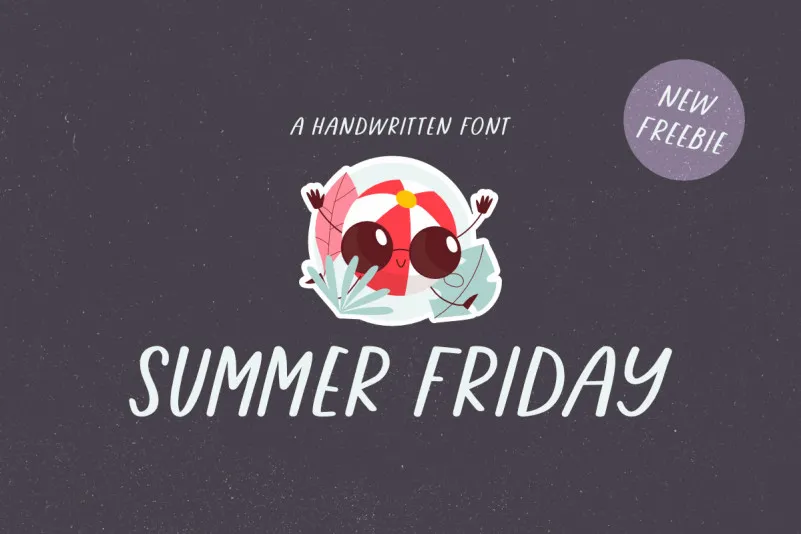
Aqui está uma breve descrição em português para a página de download da fonte ‘Summer Friday Font’: Descubra alegria no seu próximo projeto com o ‘Summer Friday Font’, uma fonte leve e divertida desenvolvida pelo designer jimtypestudio. Através de seus traços elegantes e tipografia cursiva, você pode personalizar mensagens de felicitações, convites e frases memoráveis para um toque único e alegre. A fonte ‘Summer Friday Font’ está disponível em todas as letras maiúsculas, garantindo uma aparência clean e moderna que se adequa perfeitamente a vários propósitos. Seja para criar mensagens de felicitações para festas ou eventos especiais, criar design de merchandising personalizado ou apenas adicionar um toque especial a qualquer projeto em seu dia a dia. A ‘Summer Friday Font’ é uma escolha inteligente para quem busca uma fonte leve e divertida que não demite. Seja você um designer gráfico, criador de material de marketing ou mesmo alguém que cria coisas nas horas vagas, este fonte se destaca como a forma perfeita de dar um toque único aos seus projetos. Junte-se à crescente comunidade de designers e artesãos que estão aproveitando os benefícios deste fonte única e divertida. Se você está procurando por algo mais leve, alegre e pronto para ser incorporado em seu próximo trabalho, ‘Summer Friday Font’ é o seu companheiro perfeito.